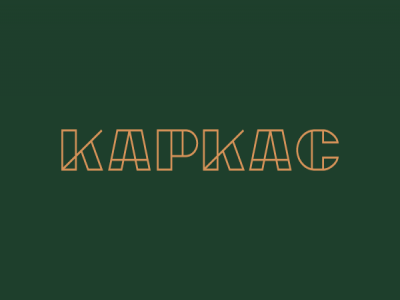
Шрифт Каркас
В процессе проверки одного из падаванов нарисовались буковки. Глобального назначения нет, думаю допилить и на стоки. Что скажете? (люблю всякие чертежные штуки)